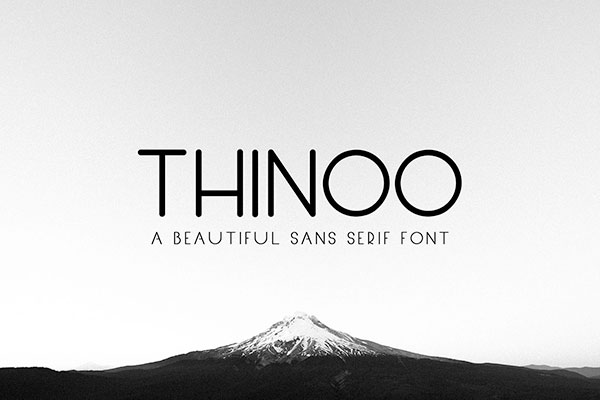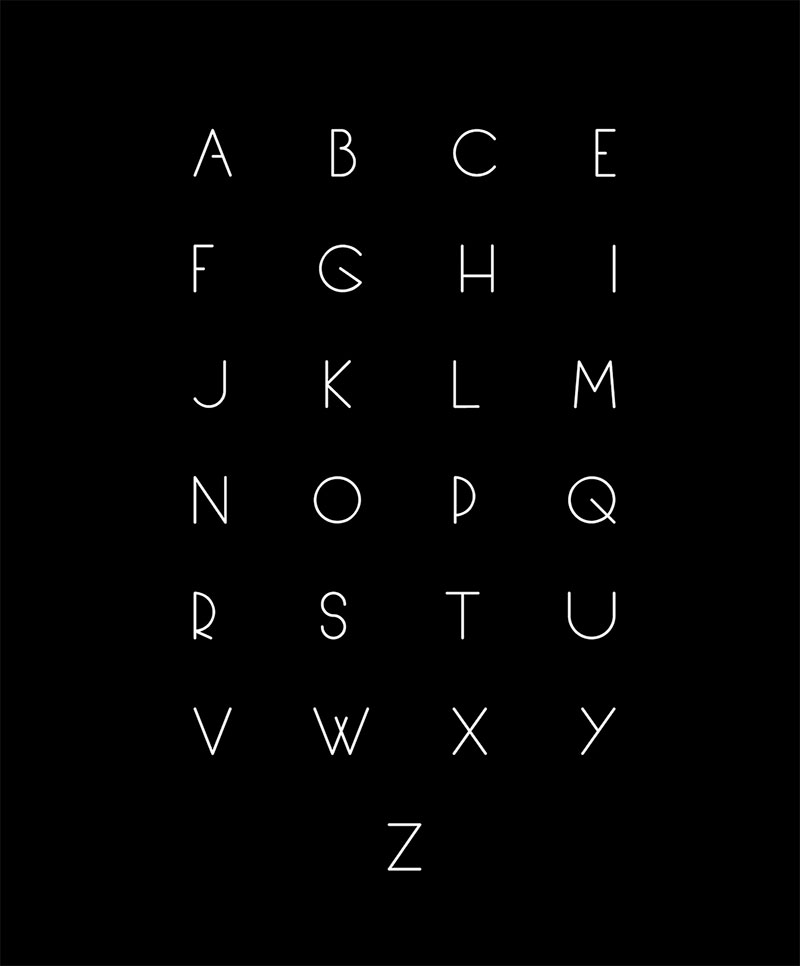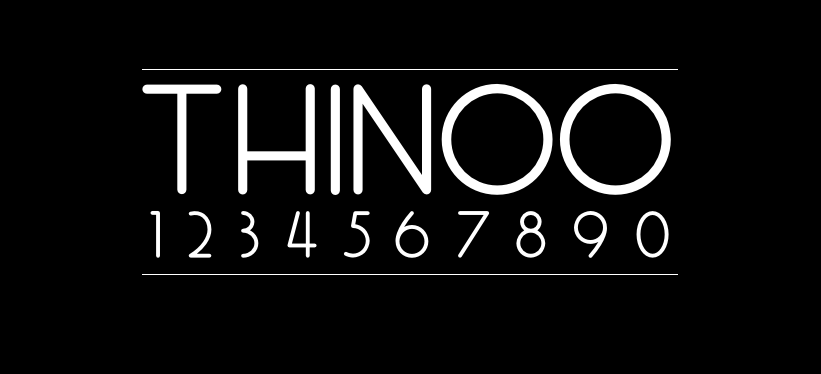
THINOO
THINOO字体介绍
Thinoo是巴基斯坦的设计师Nauman Altaf创作的一款干净而现代的免费sans serif英文字体,具有纤细而醒目的样式 。它包含大写,小写,数字,标点和符号。Thinoo字体将在简历,徽标,网站,品牌材料,T恤,印刷品,名片,海报,摄影、女性产品等方面发挥出色的作用。
该字体包含thin和bold两种粗细,虽然是这么命名的,但是自由君感觉bold还是依然很纤细的。
THINOO字体应用示例